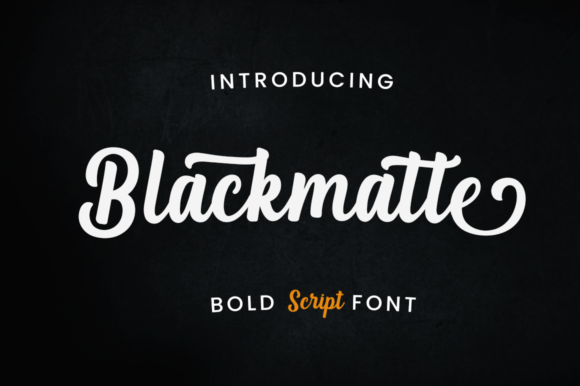
Название: Blackmatte Font (2021)
Blackmatte - это элегантный шрифт с современной атмосферой и безупречной формой, вдохновленный нестареющей классической каллиграфией. Не слишком тонкий и не слишком толстый, сбалансированный и разнообразный, этот шрифт создан для того, чтобы подчеркнуть красоту ваших проектов.